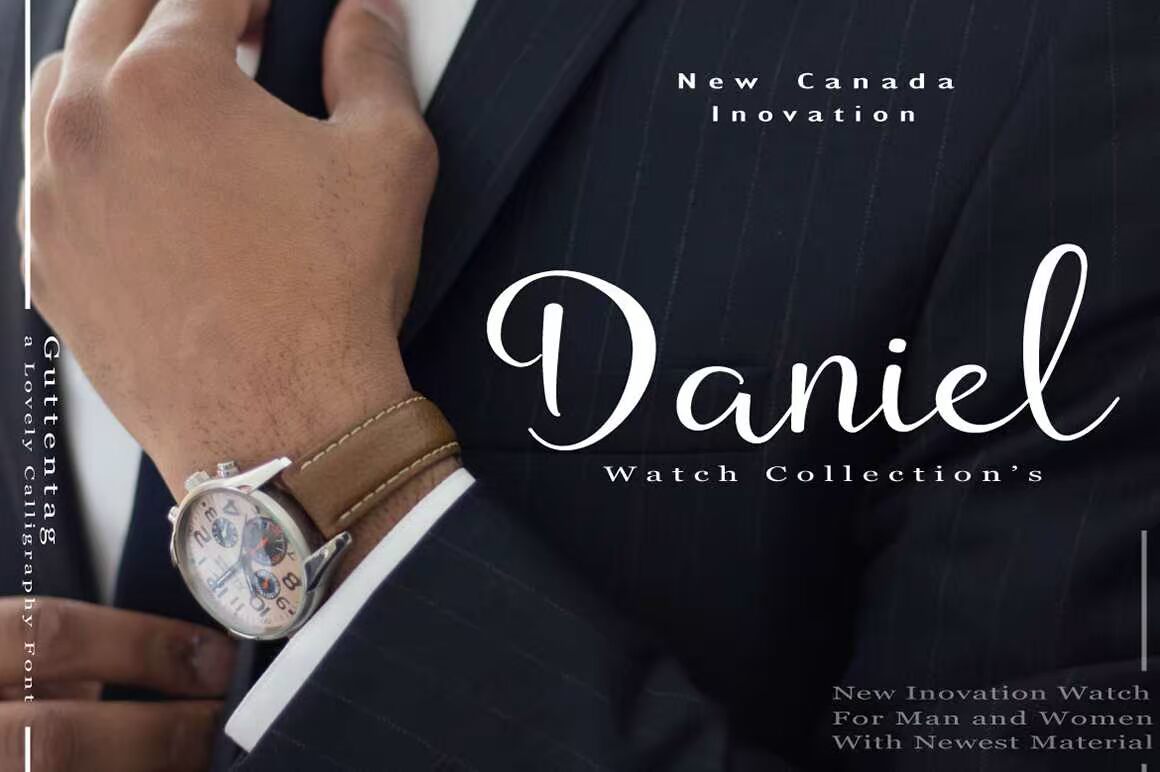
Guttentag字体优雅可爱。Guttentag源自德语“Guttentag”,意为“oodafernon”。Guttentag字体非常适合您的所有业务和设计项目,包括婚礼活动、徽标、品牌、签名、海报、报价、,还有更多。Guttentag字体字体优雅可爱。Guttentag来自德语“Guttentag”,意思是“GoodTernoon”。Guttentag字体非常适合您的所有业务和设计项目,包括婚礼活动、徽标、品牌、签名、海报、报价等。